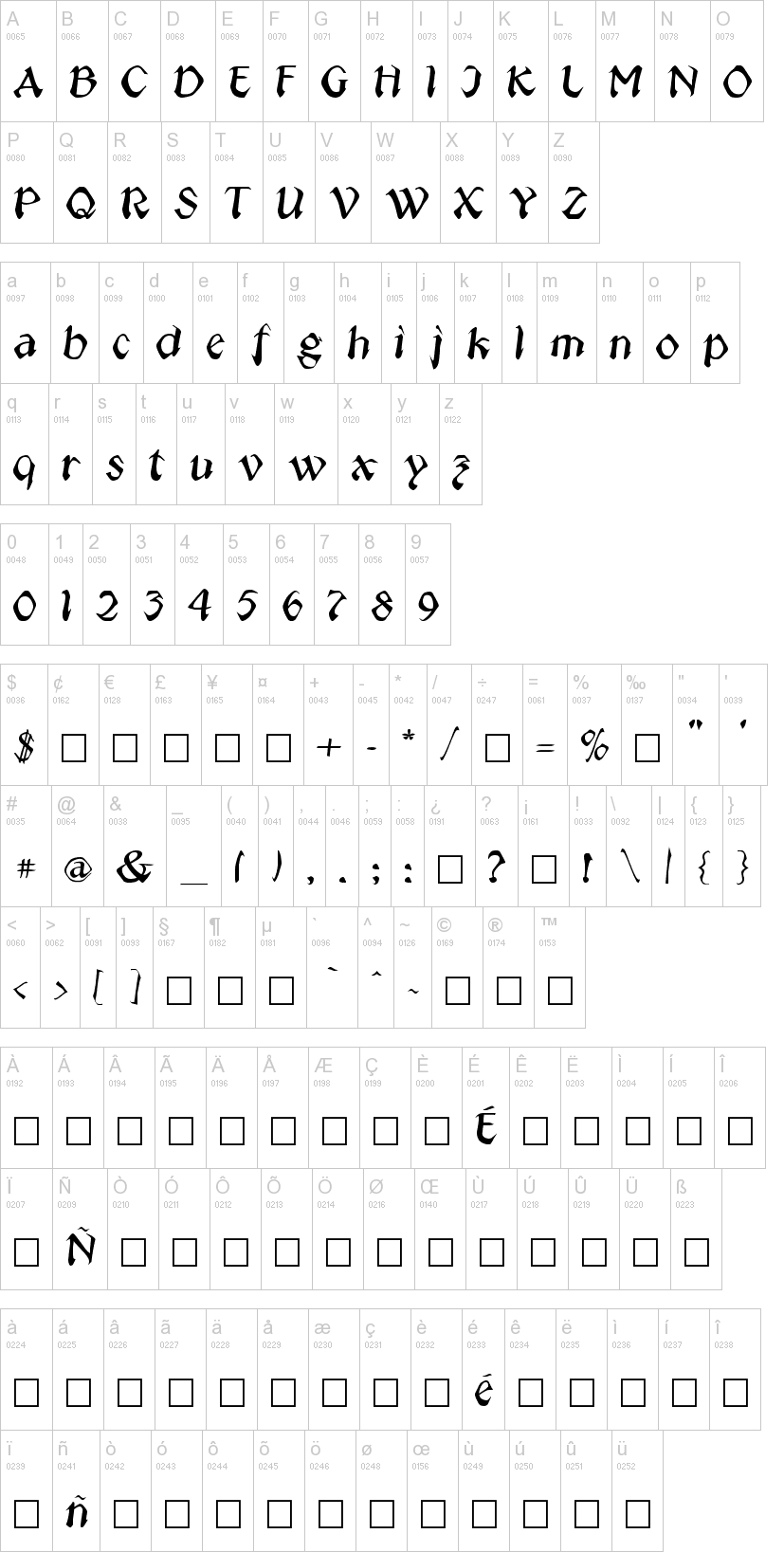
Jeepney是一种免费开源字体,由Philip Paraan设计。这个字体的灵感来源于菲律宾的传统公交工具Jeepney,这种车辆通常被涂上鲜艳的颜色和华丽的装饰。因此,这个字体的设计极具菲律宾文化特色和风格。 Jeepney字体具有浓重的手写风格,同时还融合了现代化的设计元素,使得这种字体在不同的设计场景中都可以得到很好的应用。它具有较宽的字母间距和大写字母的横杠,使得它在小字号下仍然很易读,同时也很适合用于标题和宣传海报等场景。 Jeepney字体家族包括了Regular、Italic、Bold和Bold Italic四个字重,同时还有丰富的字形和多语言支持,可以满足不同设计需求的使用。内容介绍
Jeepney是一款非常不错的手写艺术字体,具有很好的视觉感,适合于文化类的宣传设计、商业类品牌的广告和产品包装设计以及个性化文字排版等较多场景。